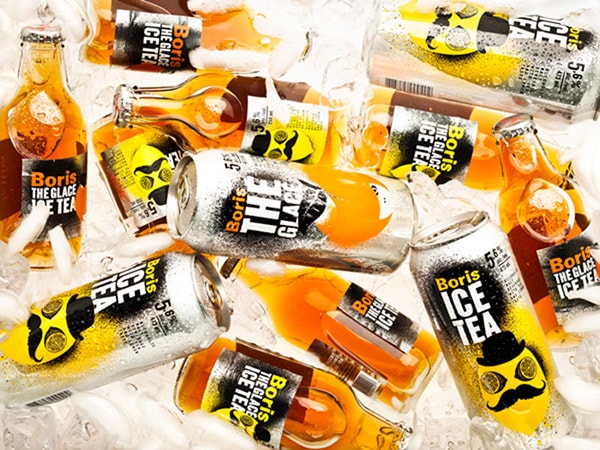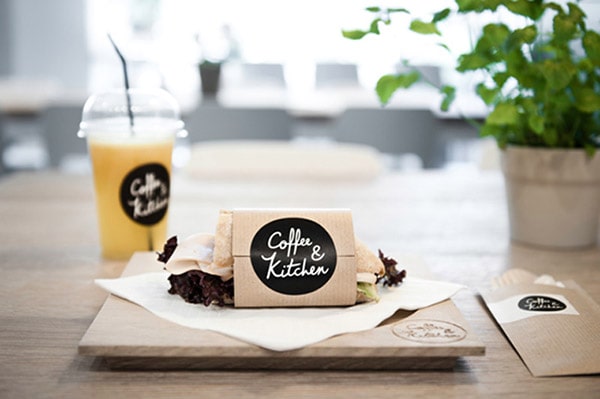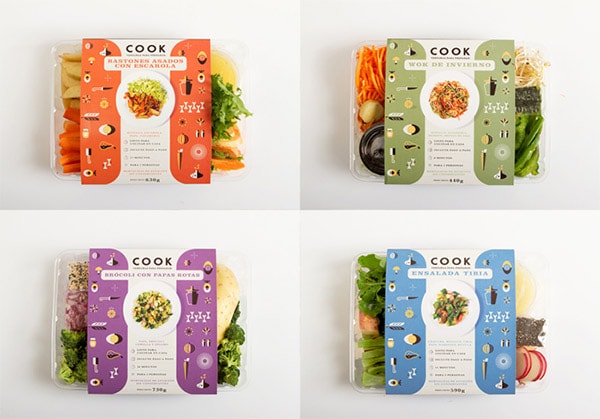
20 sublimes packagings qui misent sur la typographie
Le packaging demeure encore et toujours un élément incontournable pour véhiculer l’image de votre produit. Non content de donner envie à l’acheteur, celui-ci a pour mission de traduire votre vision du dit produit. En voici une petite sélection.
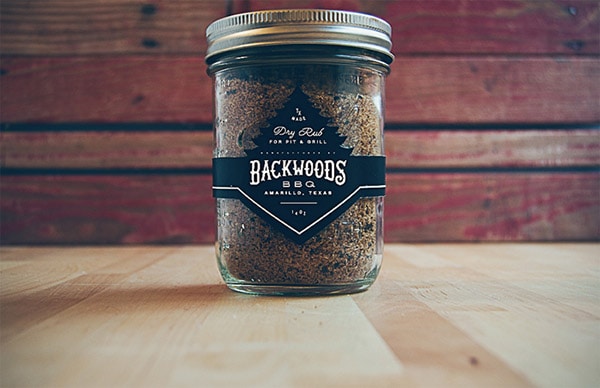
De la sauce barbecue pour hipster.
Quand vous produisez quelque chose, le design du packaging de vos produits joue un rôle essentiel si vous voulez survivre dans le marché concurrentiel actuel. Pour un designer, quand il est question de la conception d’un emballage, la typographie doit être l’une des premières choses qui frappent les esprits. Celle-ci se doit d’être aussi lisible que possible (et attrayante) afin que les gens soient attirés par cette dernière au premier regard. Dans notre vie quotidienne, nous voyons quantité d’exemples de packagings. Plus ou moins réussis, beaucoup de « tout-venant » mais peut-être pas assez de « beaux emballages » qui soient à la hauteur de ce qu’ils contiennent. Une lubie de graphiste que d’aimer un produit aussi pour sa boîte ? Peut-être bien…
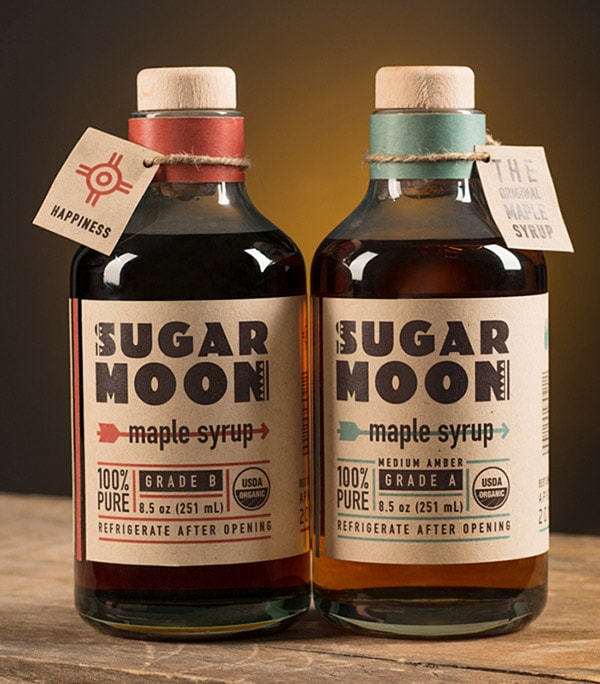
Cet emballage est inspiré de la culture amérindienne, qui utilisait le sirop d’érable avant la colonisation.
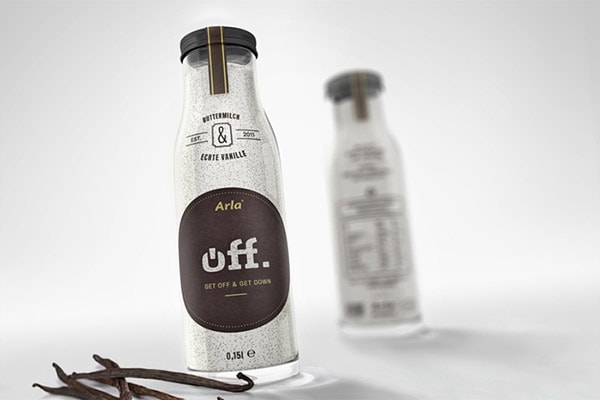
Du lait ribot. Je le mets, car la bouteille est classe, mais je fais mon militant en vous rappelant qu’on n’est pas vraiment fait pour digérer ce type de produits une fois adulte
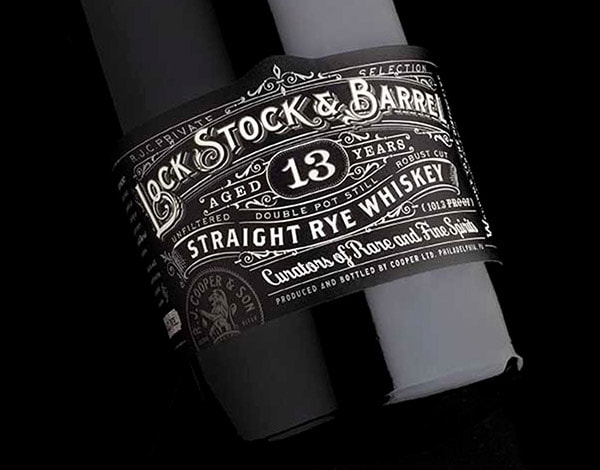
Une gamme de différents thés glacés sans alcool.
Avec une identité sobre et minimaliste, cette marque est le produit à elle seule.
Un packaging pour des plats cuisinés. Un poil moins typo, mais tout aussi top.
Parce que les fayots, ça peut être cool. Jusque dans l’emballage.
De la bière On appréciera le style d’avant-guerre avec la présence du zeppelin en arrière-plan.
Un soda décliné en cinq parfums. Je suis totalement fan du style épuré.
Des oignons au vinaigre de balsamique. Authentique, mais pas top pour choper.
Clin d’oeil à Sea Shepherd au passage.
La Muu, première crème glacée écologique d’Estonie.
Un style relativement classique pour un whiskey, mais qui reste une valeur sûre (le style, comme le contenu).
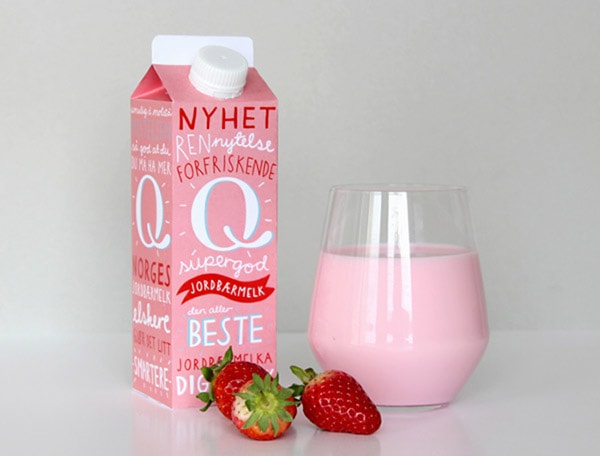
Le lait fraise, c’est bon. Mais préférez-le avec du lait d’amande.
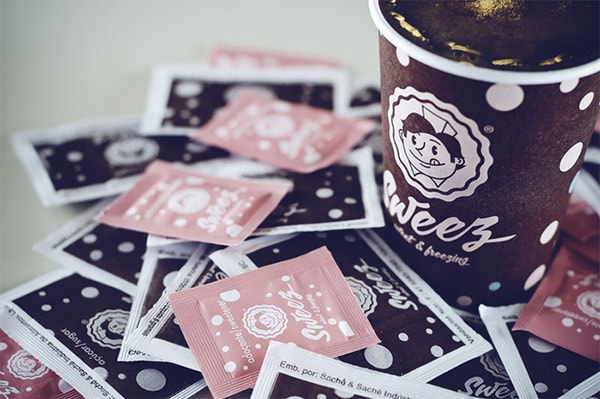
Encore de la bière.
Du thé, avec la classe d’un pot de peinture vintage. Mais la classe quand même.
Ces petits sachets carrés aux allures 50′ sont du sucre en poudre. Rien d’autre hein…
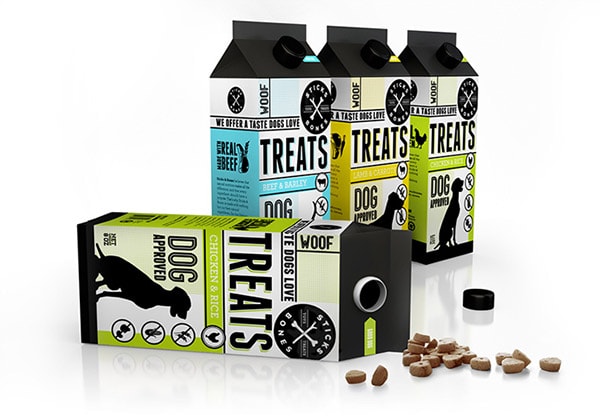
Des bouteilles pour une gamme d'épices aromatisées aux parfums de bons alcools. Juste classe.
Des friandises pour animaux de compagnie.
Et pour terminer, toujours de la bière.